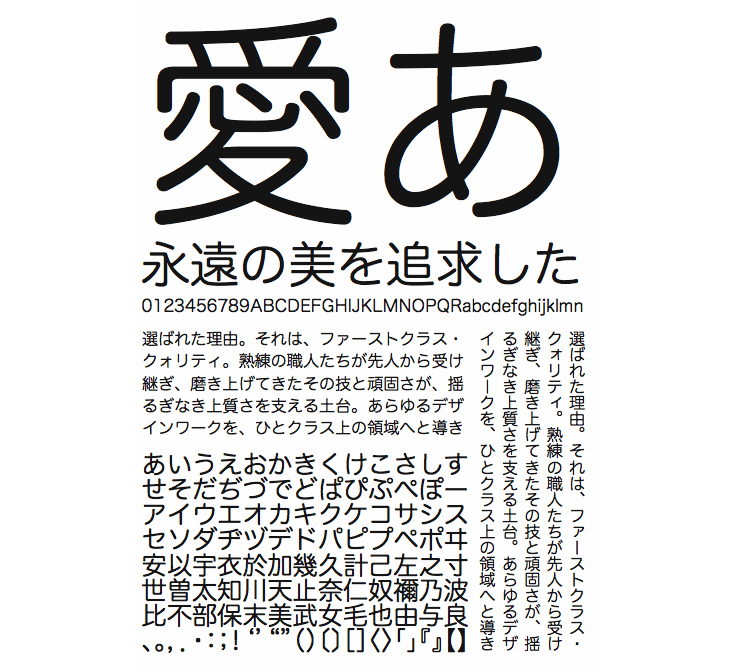
【ヒラギノ丸ゴ】広いフトコロとのびやかな字面が特徴の「ヒラギノ角ゴ」の基本デザインを踏襲して、すべての画の先端に優美な丸みを与えた柔和な書体。仮想ボディをいっぱいに使った一般的な丸ゴシックとは一線を画し、活字の伝統に根ざした骨格をバックボーンとする、あきのこない本格的な設計です。
ヒラギノ丸ゴ StdN W3